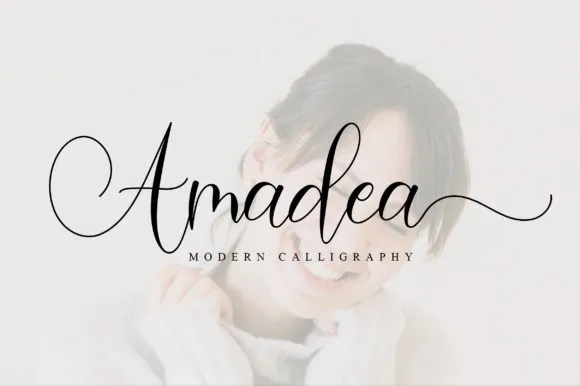
Amadea Script Font – Fonte Grátis
Amadea Script Font
A Amadea Script Font é uma escolha perfeita para os designers que buscam uma fonte escritura moderna e assertiva. Ela traz uma sensação de elegância com um toque divertido e delicado, tornando-a ideal não apenas para trabalhos profissionais, mas também para projetos criativos e artesanais. Desenvolvida pela NissaStudio, a Amadea Script é uma fonte escritura playfull e adorável que transformará seu trabalho em algo realmente notável e impressionante. Com seus caracteres dinâmicos e arredondados, esta fonte script é perfeita para criar artefatos incríveis. Seja você um designer gráfico, editor de fotos ou artesão, a Amadea Script oferece um toque único que tornará seu trabalho ainda mais único e personalizado. Esta fonte não apenas traz beleza aos seus projetos, mas também eleva o nível de sua produção criando artefatos que impressionarão seus espectadores. Descubra por si mesmo como a Amadea Script pode transformar suas criações em algo inesquecível.